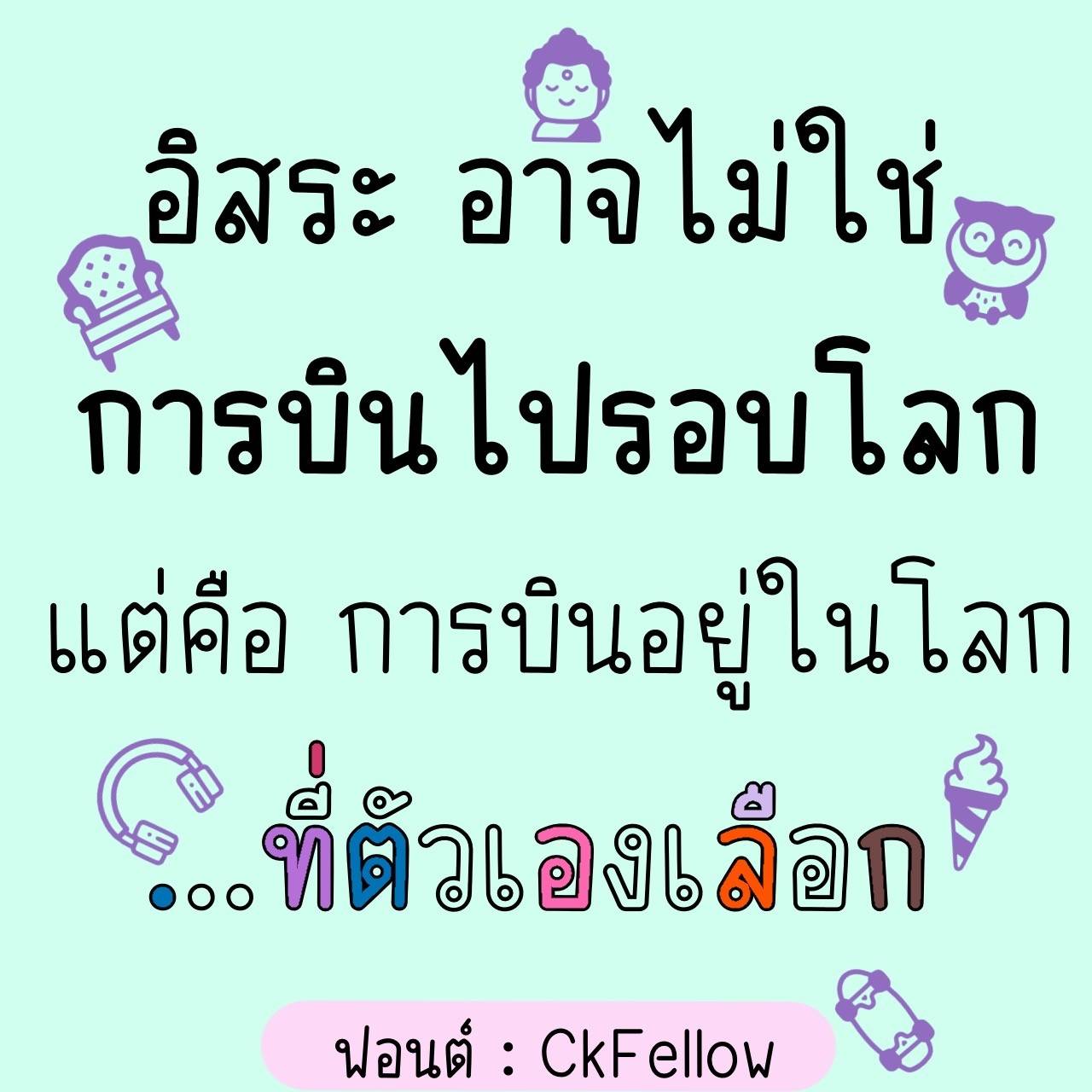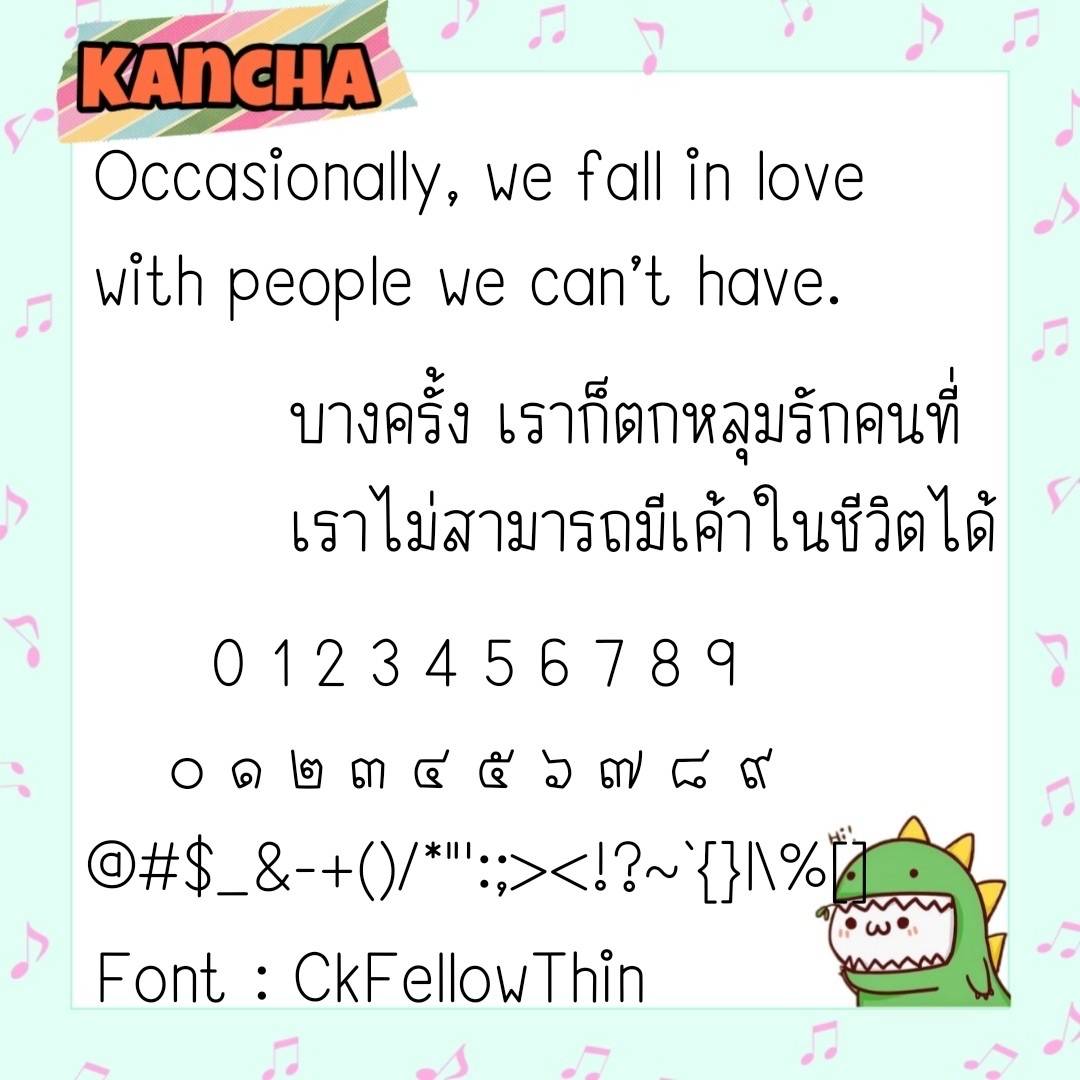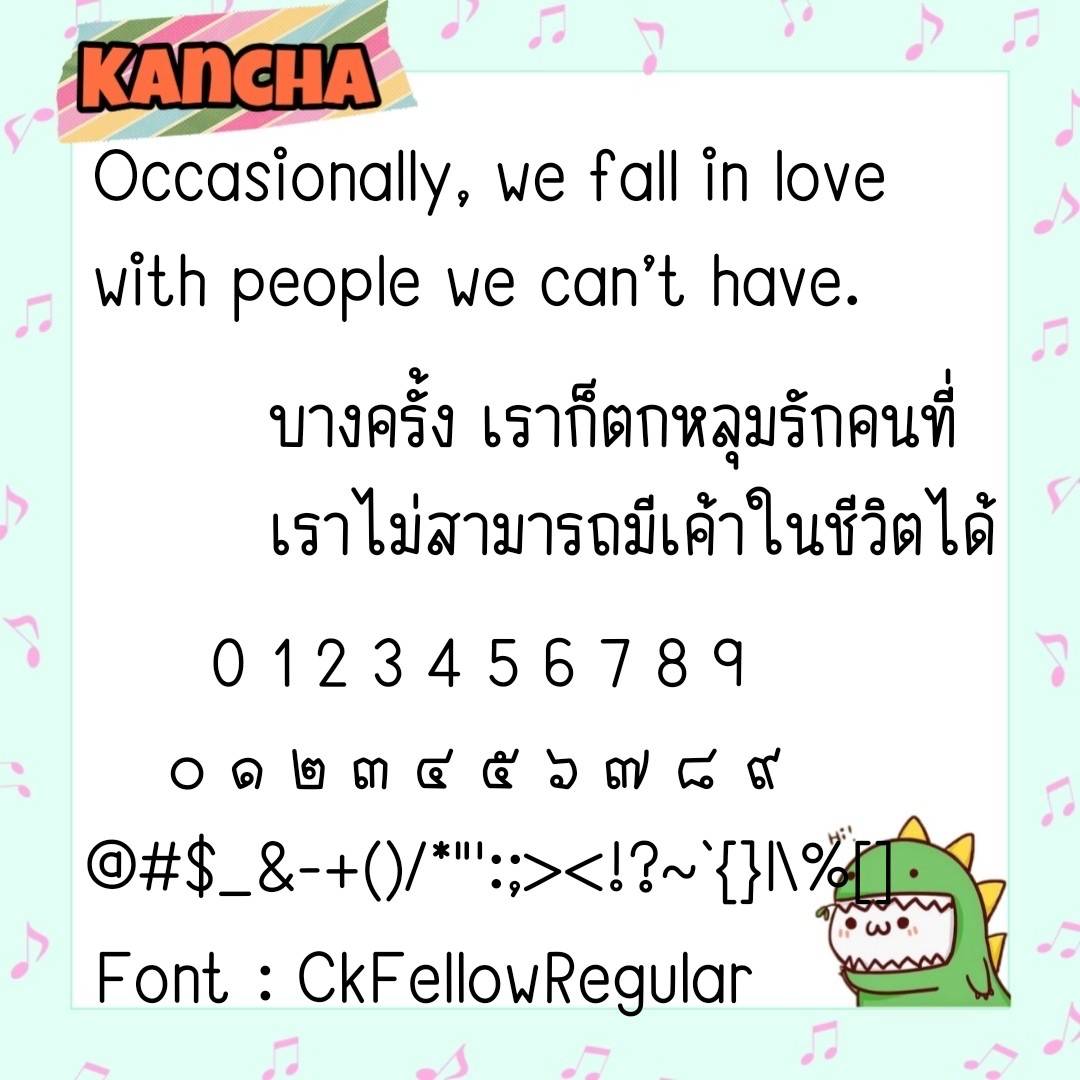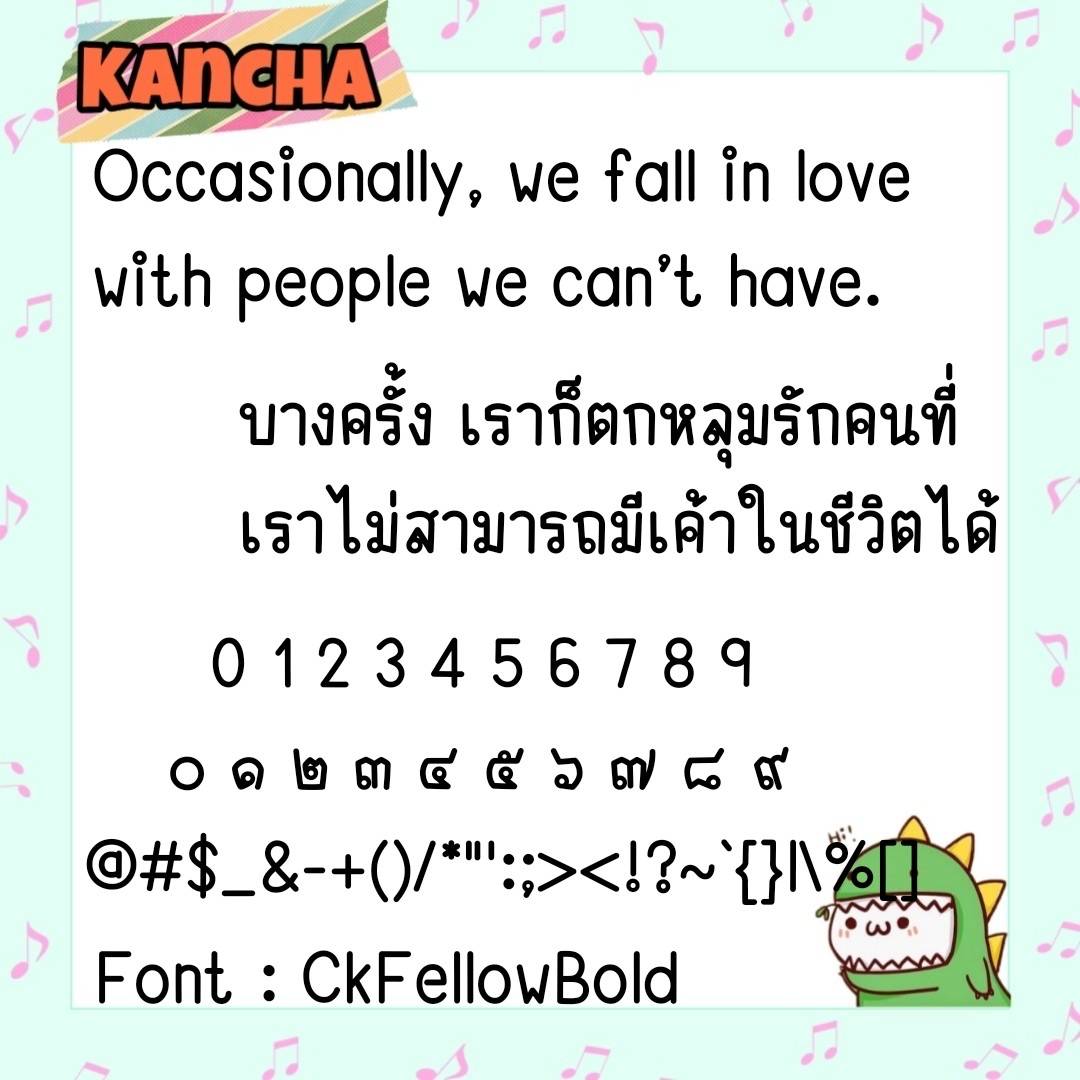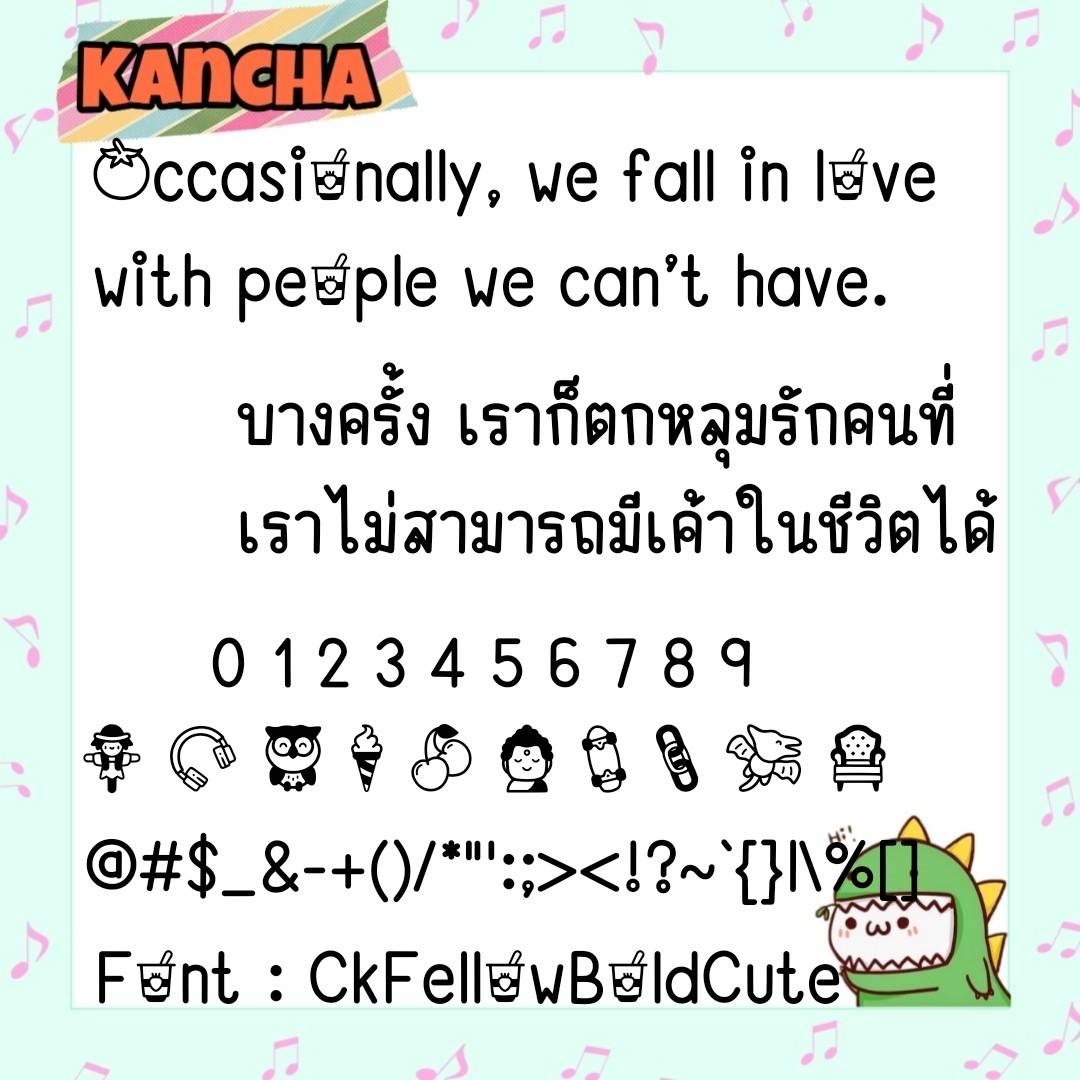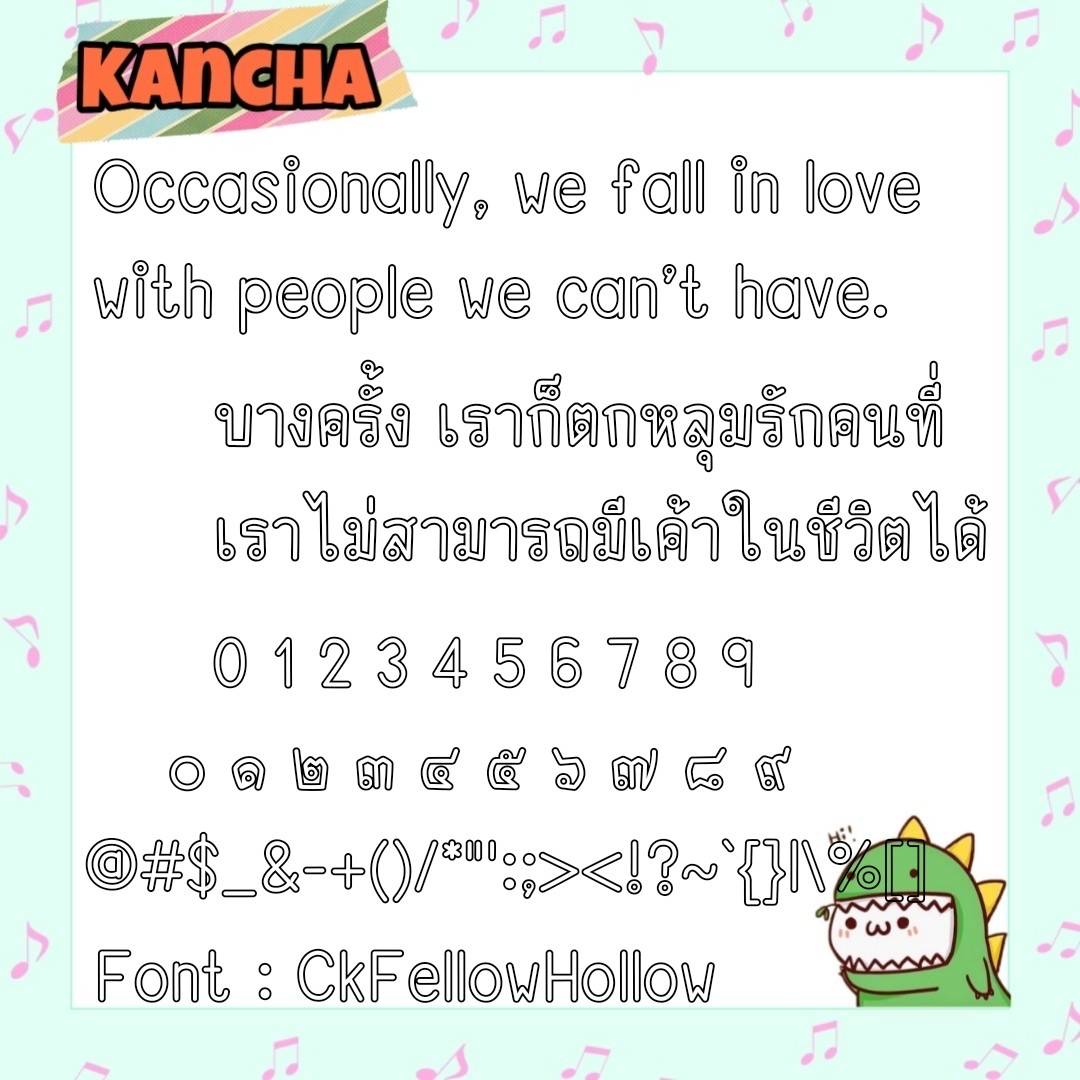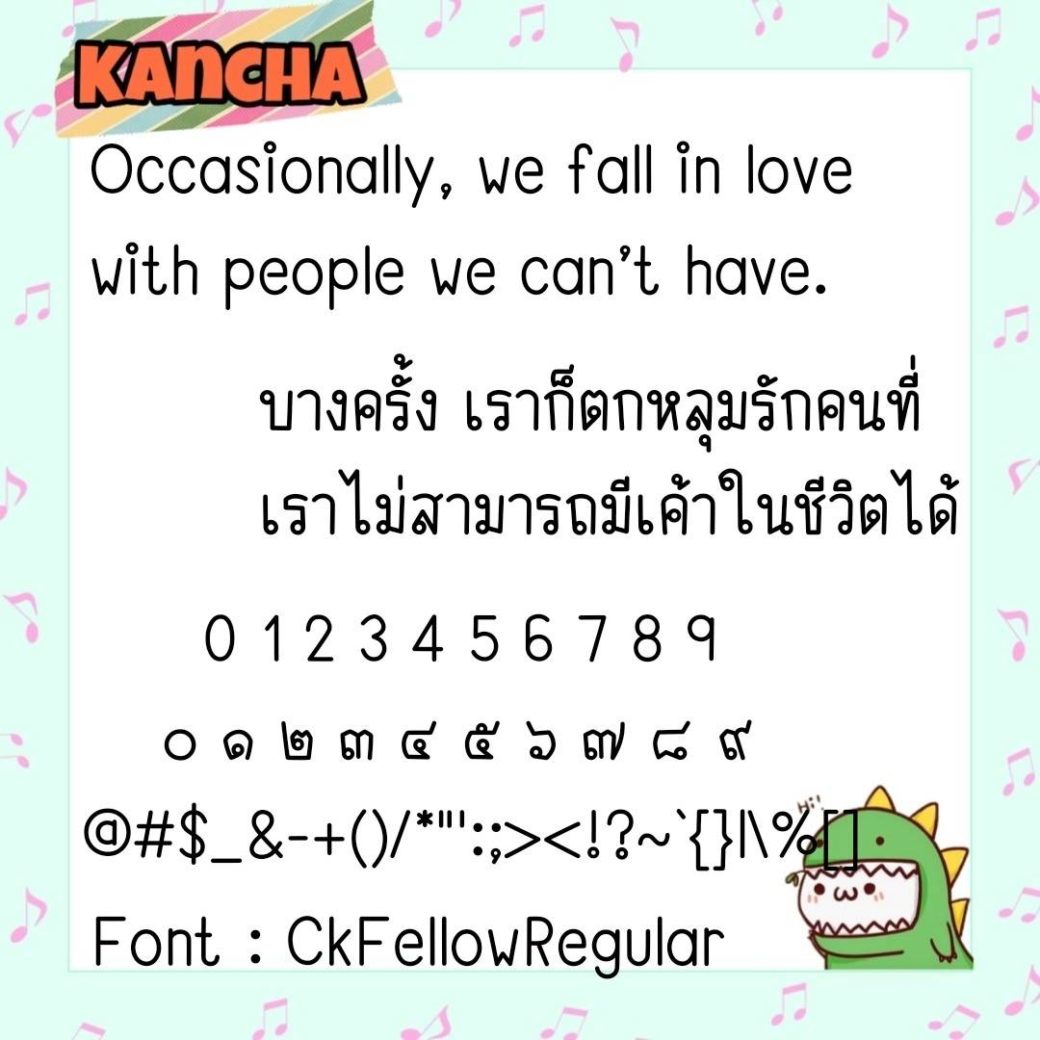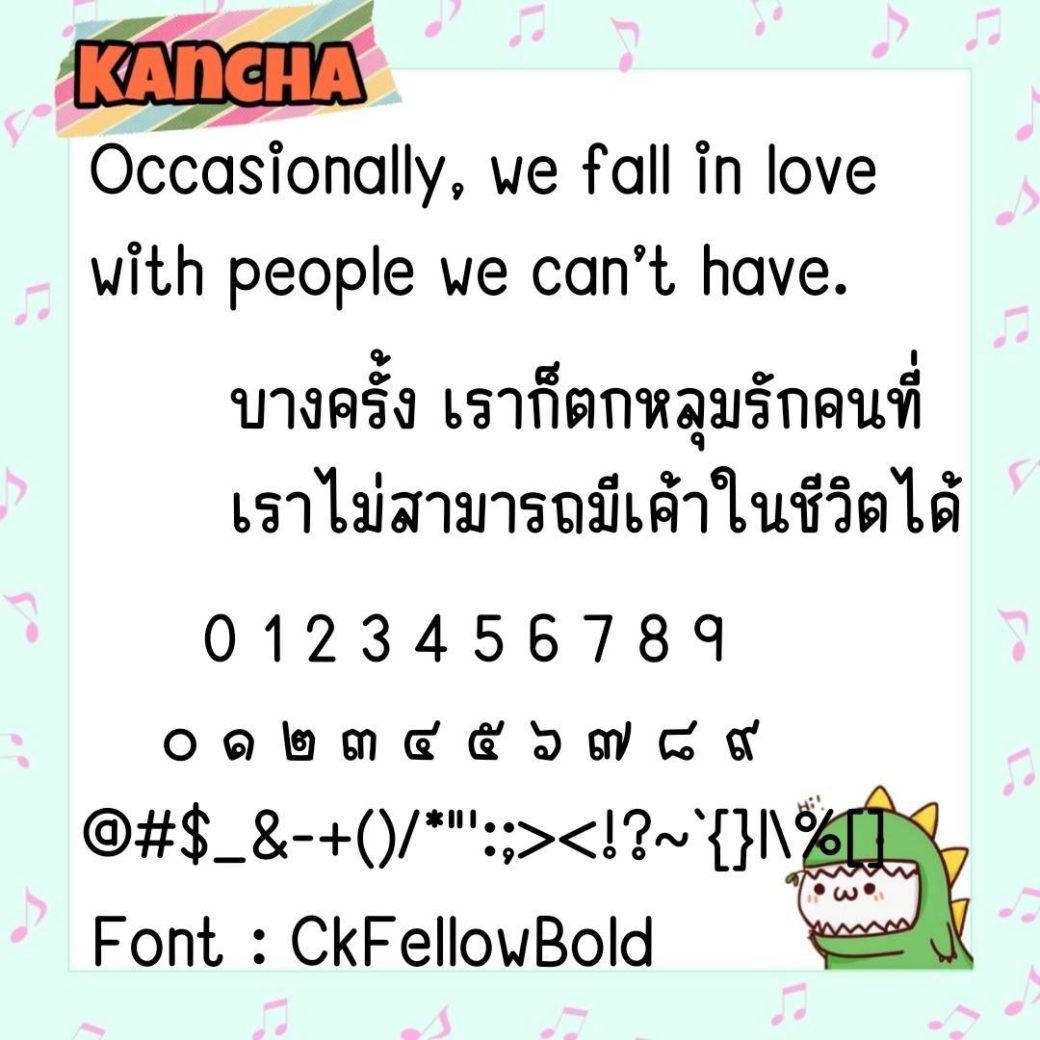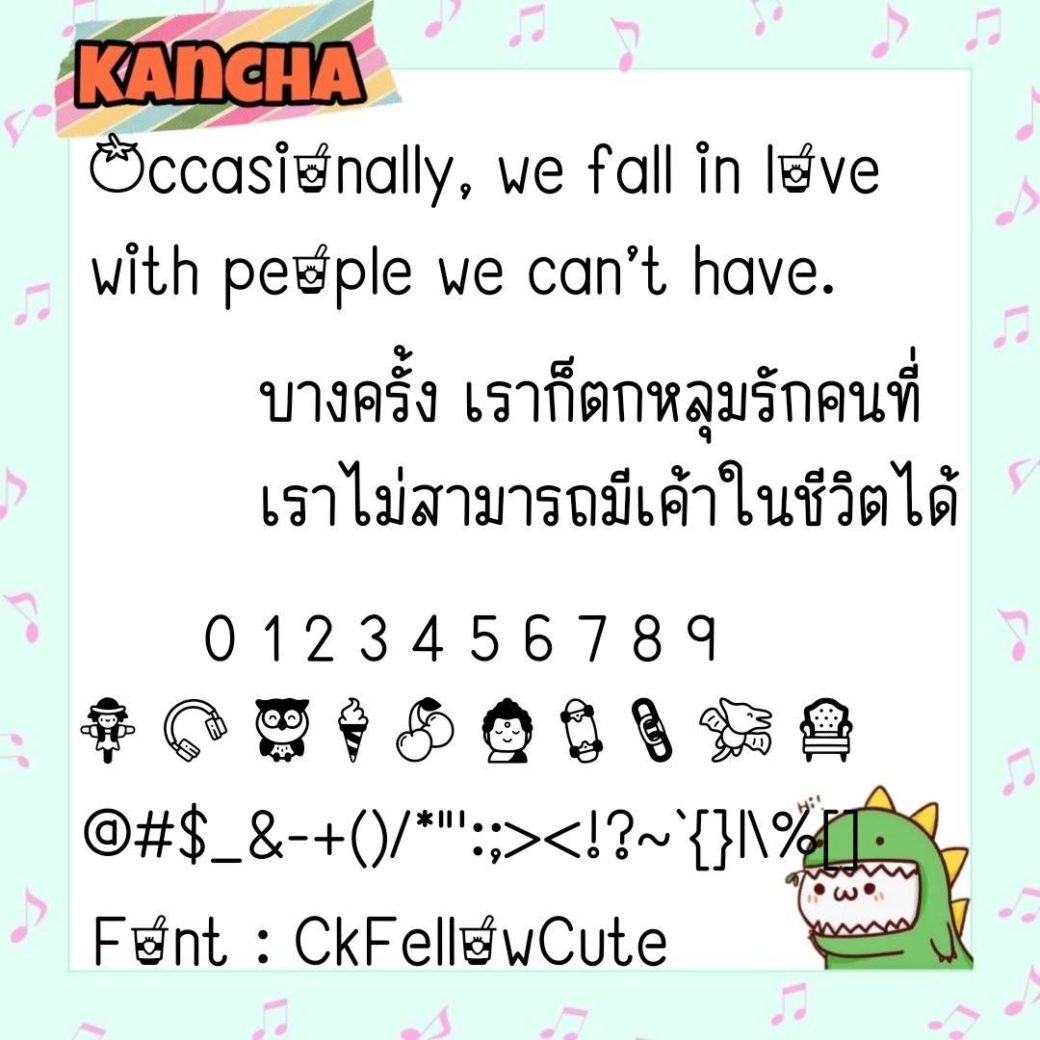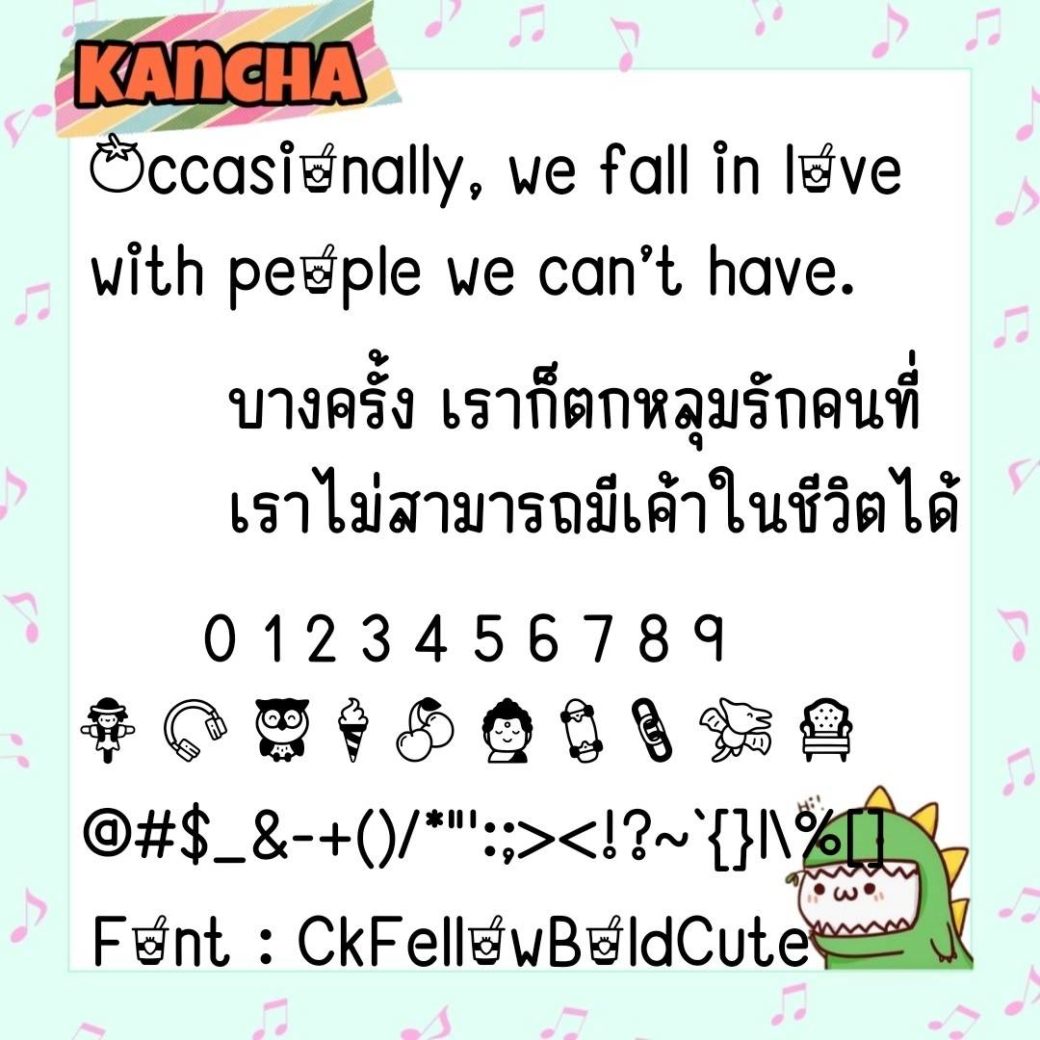
Font CkFellow
ชื่อสินค้า : Font CkFellow 💙
🔸ฟอนต์แนวอ่านง่าย ดูสบายตา
แนวกึ่งเหลี่ยมๆนิดๆ เน้นหัวกลมๆ เพื่อให้เส้นดูไม่แข็งจนเกินไป ฟอนต์นี้มีทั้งเส้นหนา,บาง,ปกติ,พรีเมียมที่เป็นตัวโปร่ง ไว้ลงสีน่ารักๆ และยังมีไฟล์อิโมจิน่ารักๆแทนเลขไทยให้ในชุดด้วยค่ะ 🥰💙
🔹Easy-to-read, easy-to-read font
The semi-square line is a bit emphasizing on the round head so that the lines don’t look too stiff. This font has thick lines, thin lines, normal, premium that is transparent. put in a cute color And there is also a cute emoji file instead of Thai numbers in the set as well.🥰💙